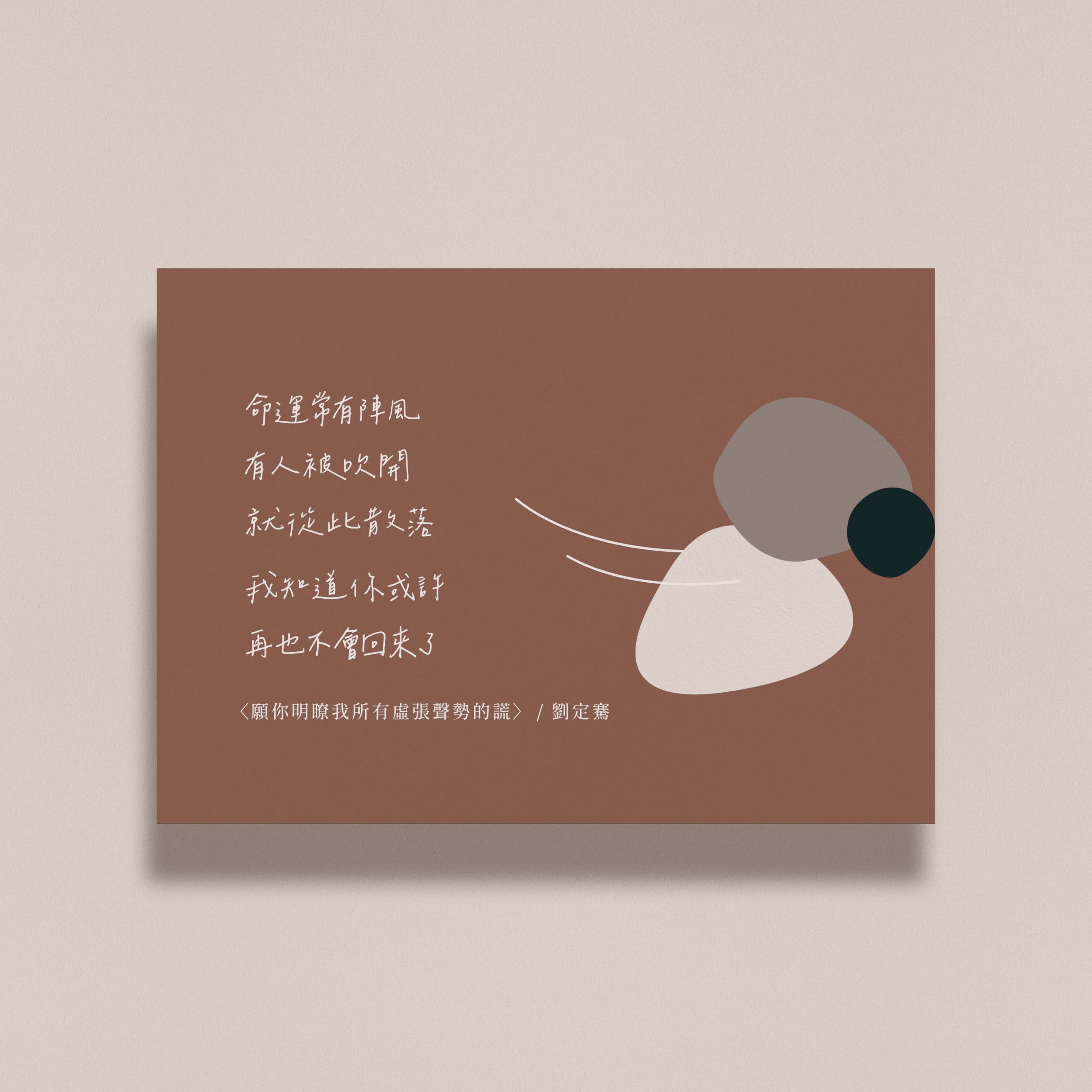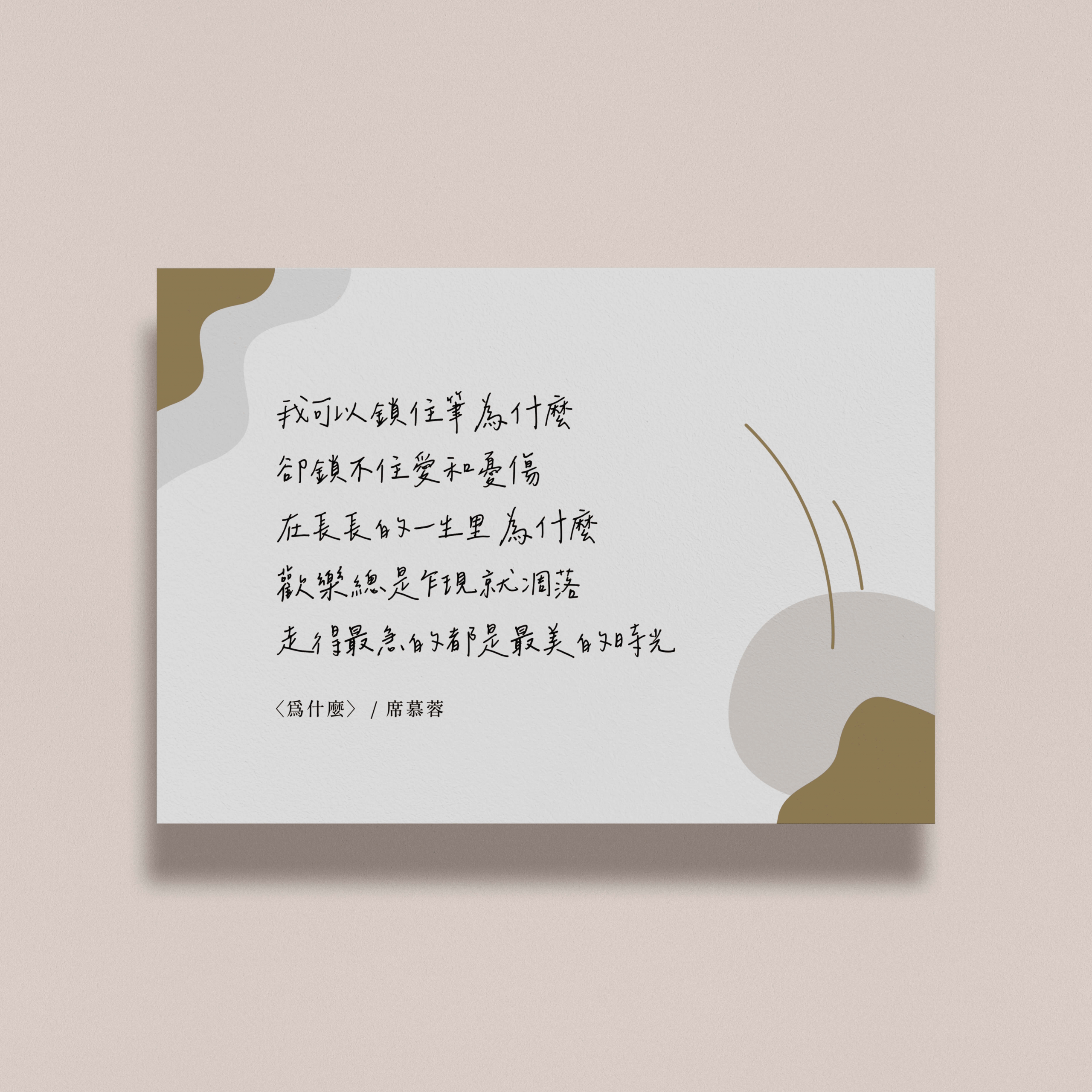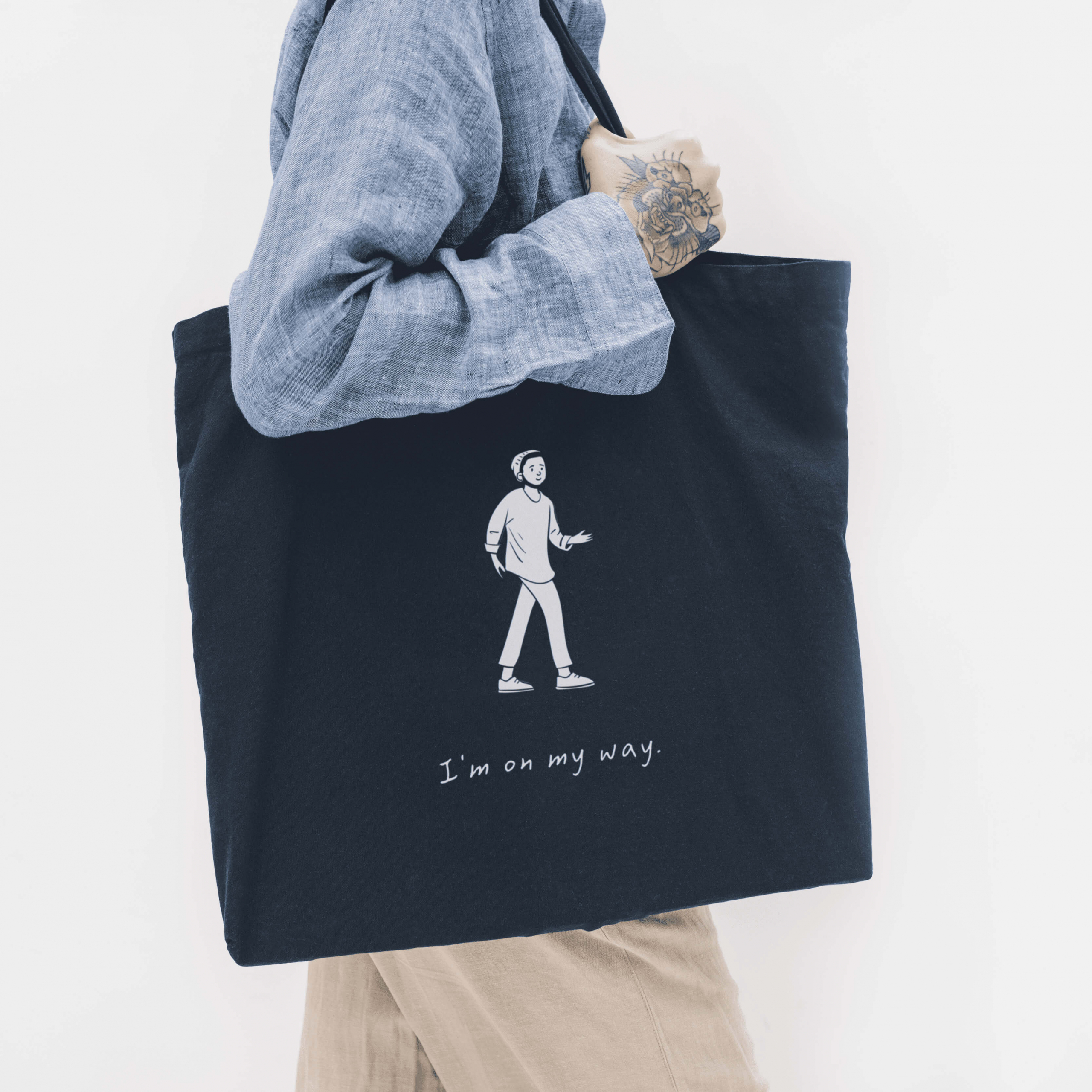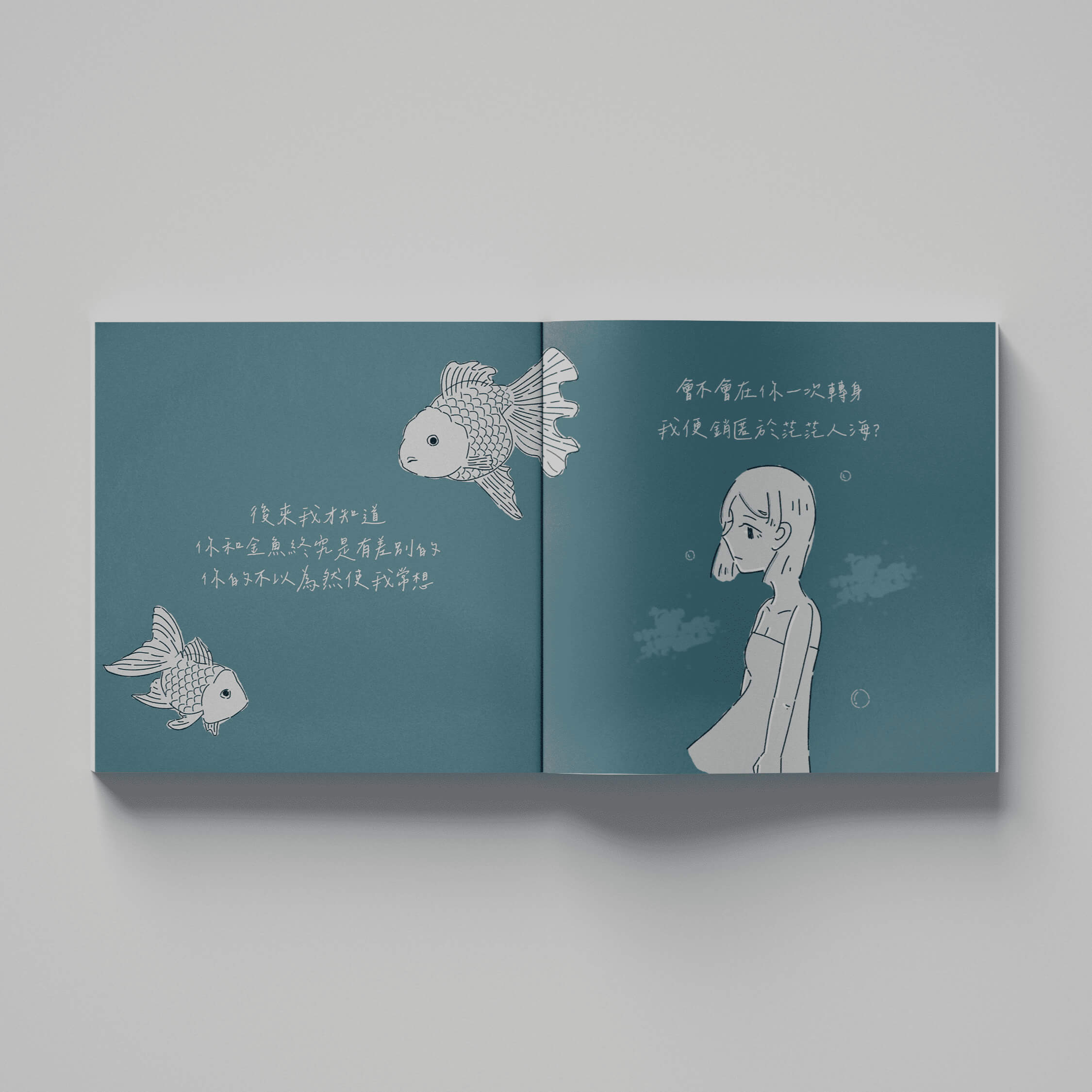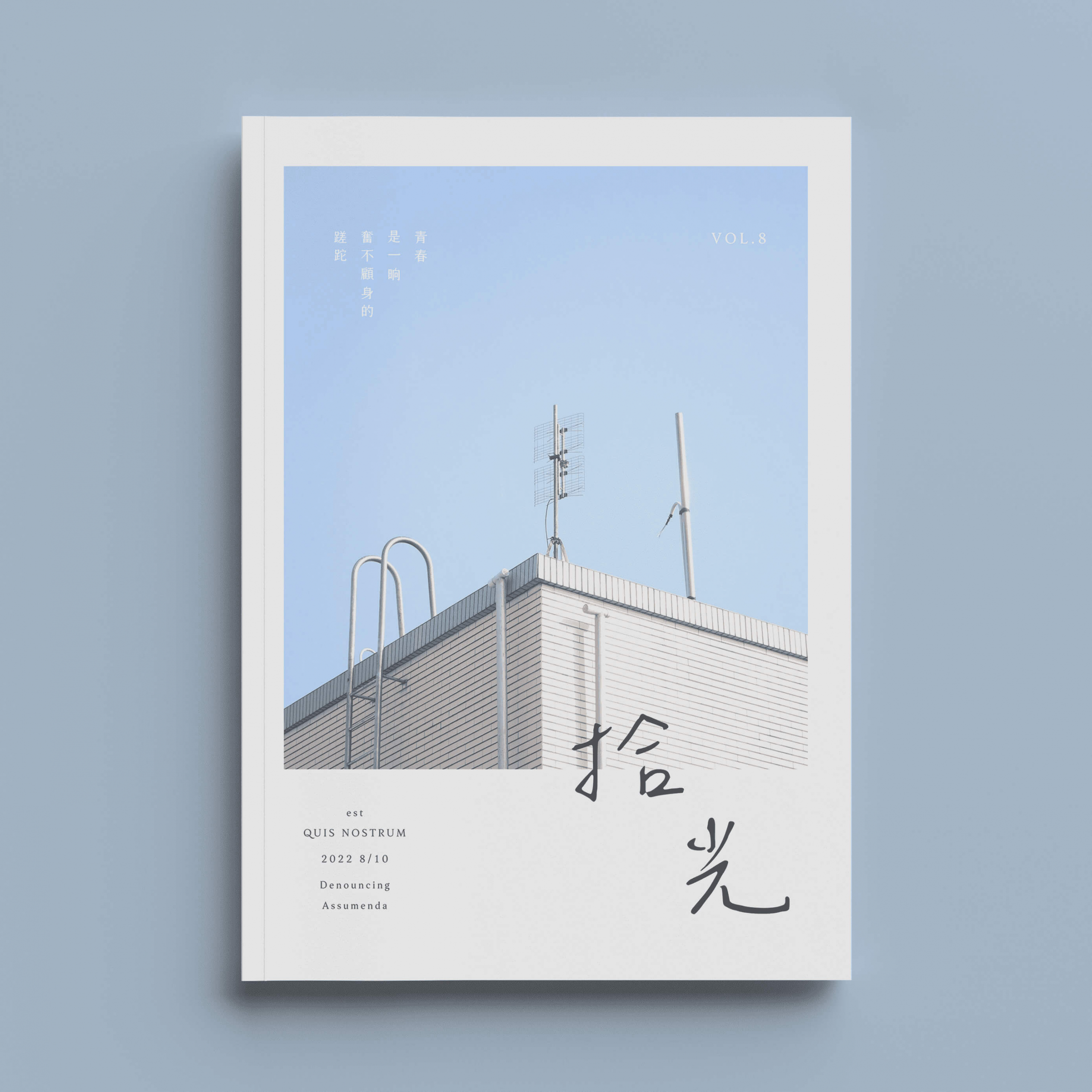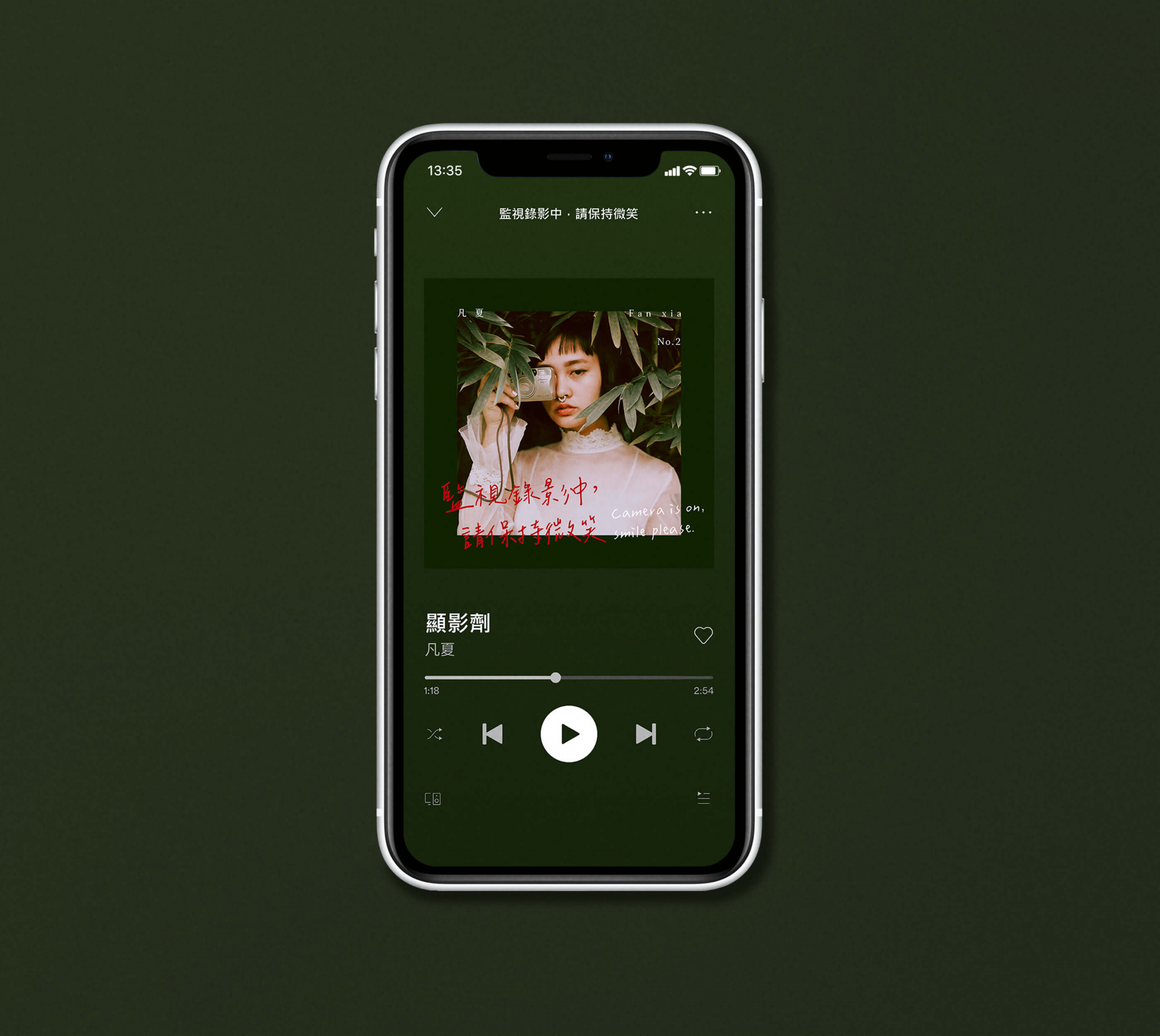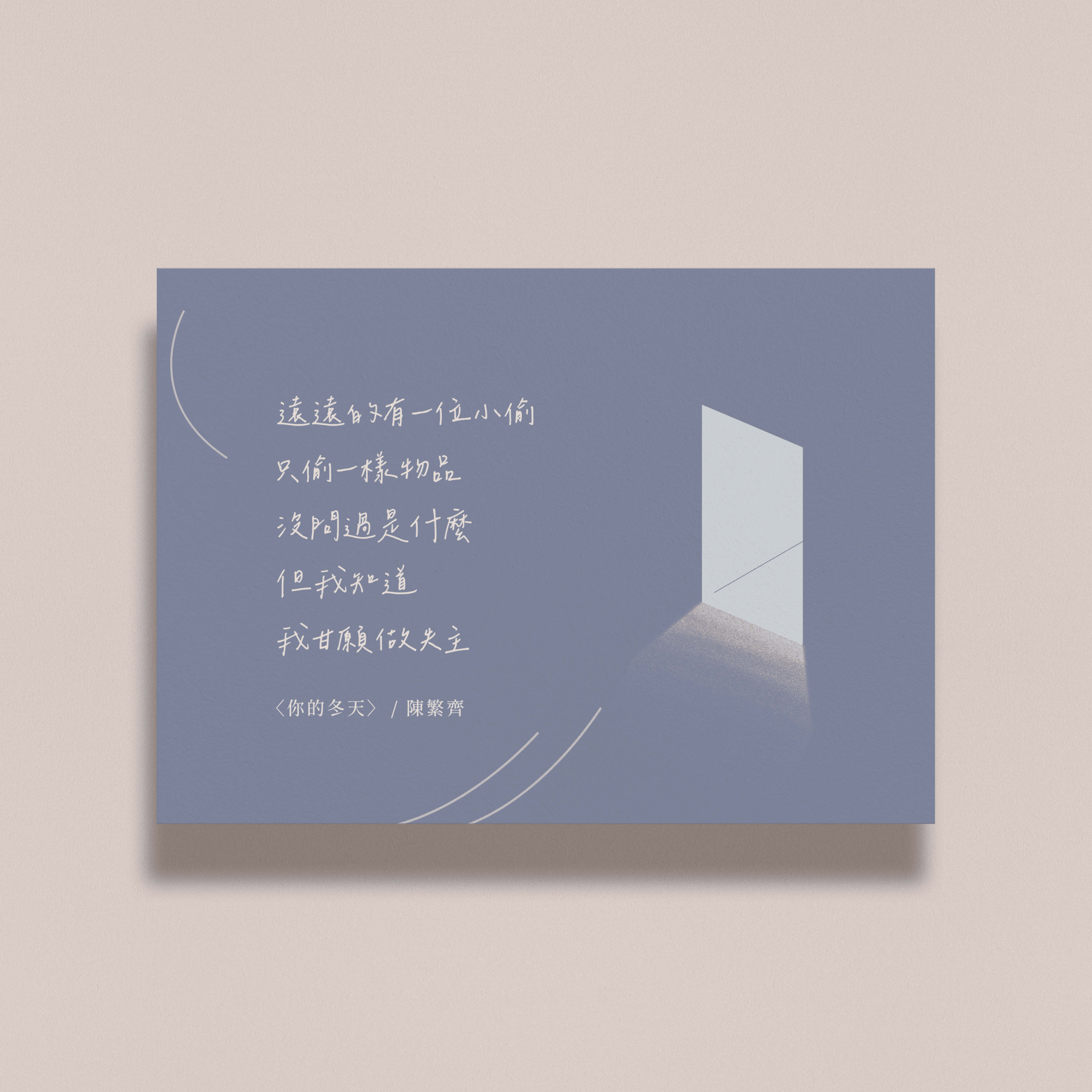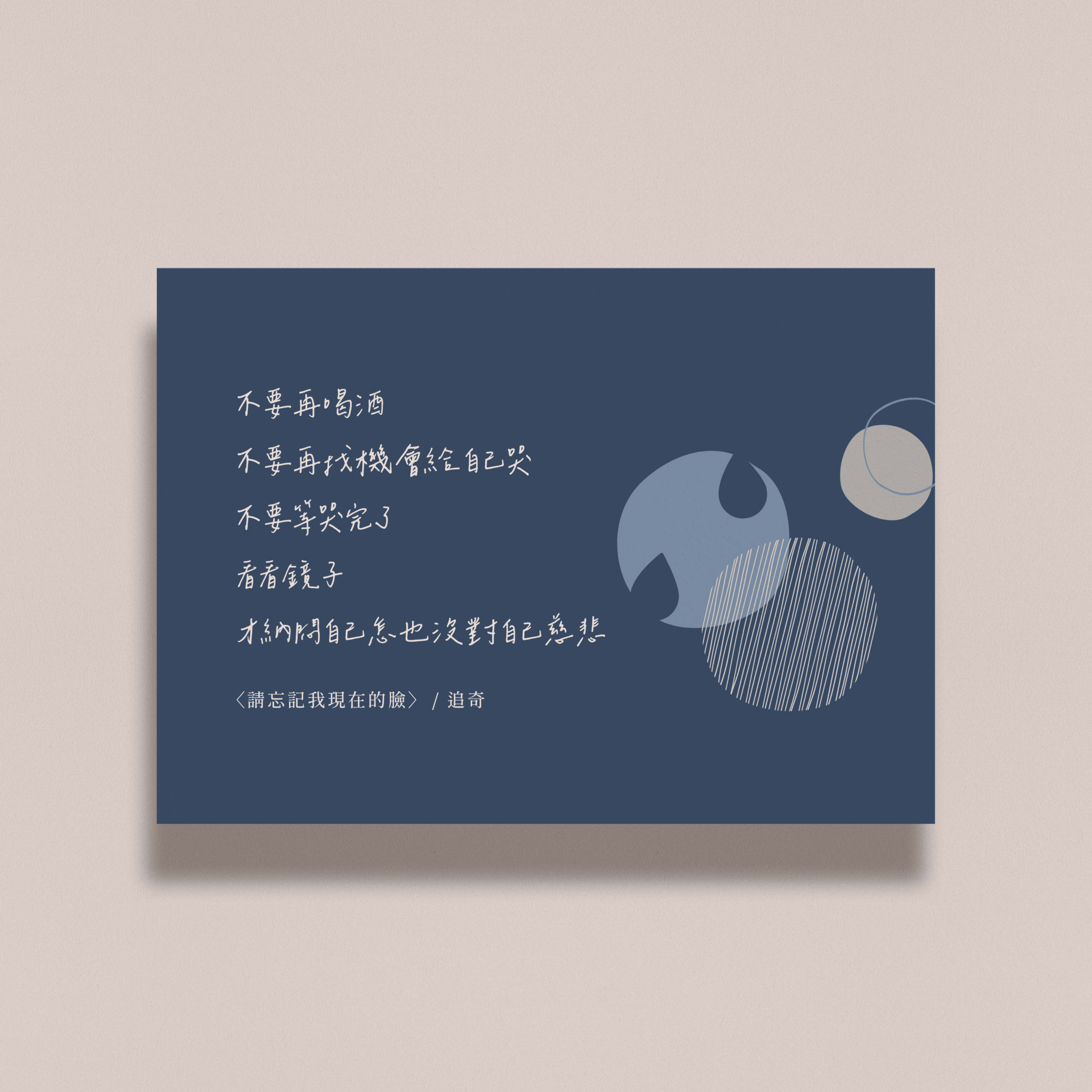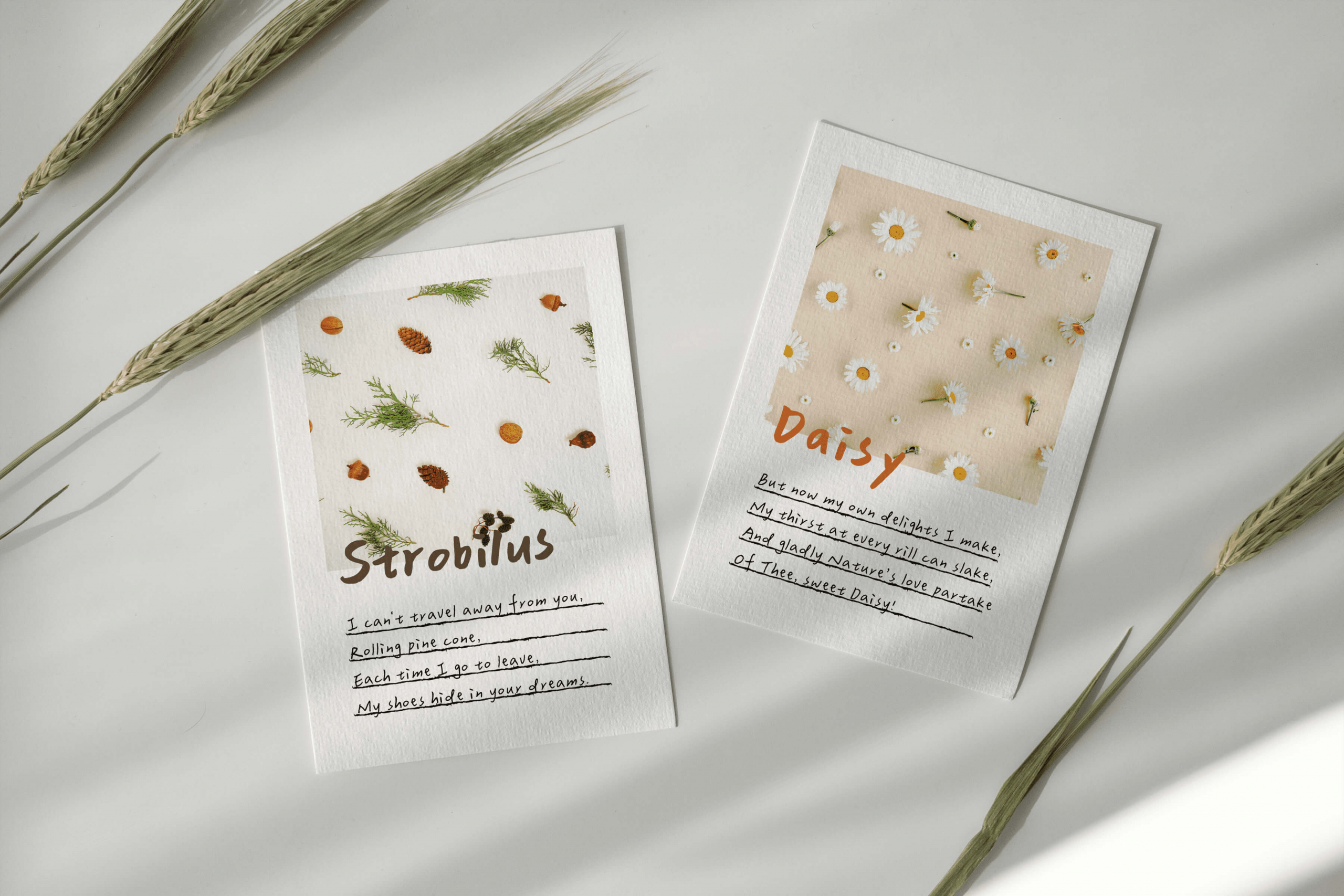
「辰宇落雁体」是我与韦辰在学校的自主学习计划,由韦辰负责书写,我进行后制而成。手写字型就像是我们将字词复写于纸上,让字迹留下,以这种近似隽永的形式封装,使被复写的日常没有保质期,也像是一种永恒的召唤,在任何无法抵达的以后,都能为你书写成篇。
制作故事
欸,你要不要做手写字体?
去年的八月,那阵子我开始关注字型相关议题,在一次偶然看到韦辰的手写字后,萌生出要是自己也能做一套手写字体,真是太酷了!而适逢 108 课纲的我们,课纲强调自主学习的精神,正巧让我们有机会发展计划,于是,手写字体的钻研之路就这样开始了⋯⋯
但「万事起头难」,我们一开始的起步并不这么顺利,对于字型不太熟悉的我们于是开始搜寻相关信息,忽而地想到,YouTube 频道「壹加壹」与 justfont 推出的粒线体,我们写信请教手写字型的前期制作方向,获得了他们真诚的回复,他们向我们分享制作字型需注意的要点,也在计划过程中提供我们咨询与技术指导,成为很大的助力。
我们最初是在在线字型制作平台──「守写字网站」习得手写字型的制作流程,后来为了更大程度的制作自由,我们尝试拆解流程,并以自己的方式进行制作,然摸索的过程并非一蹴可及,在那段期间的每周四,我潜心钻研的同时,韦辰就在一旁书写,两个人窝在图书馆的角落为心中的理想并肩努力着,制作字体是枯燥的,日复一日的书写、修改与后制,现在想想,我们还挺浪漫的,为了完成理想,不惜代价的绕了点路,也有好几次泄气的想着,或许真的做不出来了,是对于成果的想象才让我们坚持下来。
在字体做出成果后,也陆续获得不少称赞,神奇的是,制作过程中并未觉得特别的我们,在第一次打出完整的句子时,却被感动了。若浪漫一点来说,制作手写字体这件事,似将字词复写于纸上,将字迹留下为人使用。
回想制作的契机,那句「欸,你要不要做手写字体?」在今天终于实现了,韦辰写下这些文字后也将与十六岁告别,正所谓字如其人,期望她未来回首,能在字里行间看见自己。
• 「辰宇落雁体细体2.0」正式释出
• 修正「i、j」写法以区别拼音调号。
• Ver.1.0-Monospaced「辰宇落雁体Thin」等宽版本释出。
• 辰宇落雁体发布。
亮字“几”少了横笔画
• 不同地区字形规范不同,港台地区及日韩「亮」「虎」下面是「儿」,大陆写「几」。